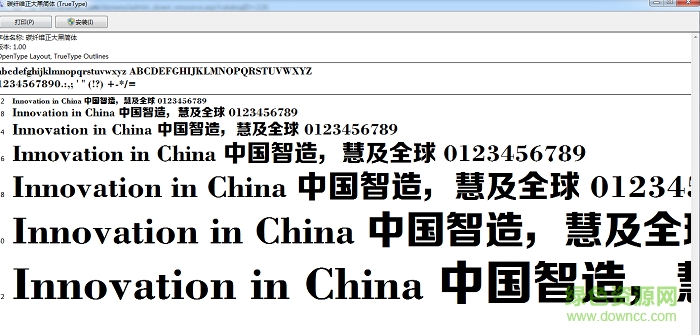
碳纖維正大黑簡(jiǎn)體是一款時(shí)尚大氣黑體字體,字形碩大,沉穩(wěn)莊重,產(chǎn)品LOGO、平面設(shè)計(jì)、雜志印刷、影視海報(bào)等領(lǐng)域都適用,需要的朋友快來(lái)綠色資源網(wǎng)下載吧!
1.因它字體較粗,橫豎粗細(xì)一致,方頭方尾,點(diǎn)、撇、捺、挑、勾也都是方的,所以又叫方體。
2.它渾厚有力,樸素大方和引人注目,很適于標(biāo)語(yǔ)、標(biāo)題,使人重視;
3.又因它結(jié)構(gòu)嚴(yán)謹(jǐn),筆劃單純,所以也常作為初學(xué)美術(shù)字練習(xí)的一種字體。